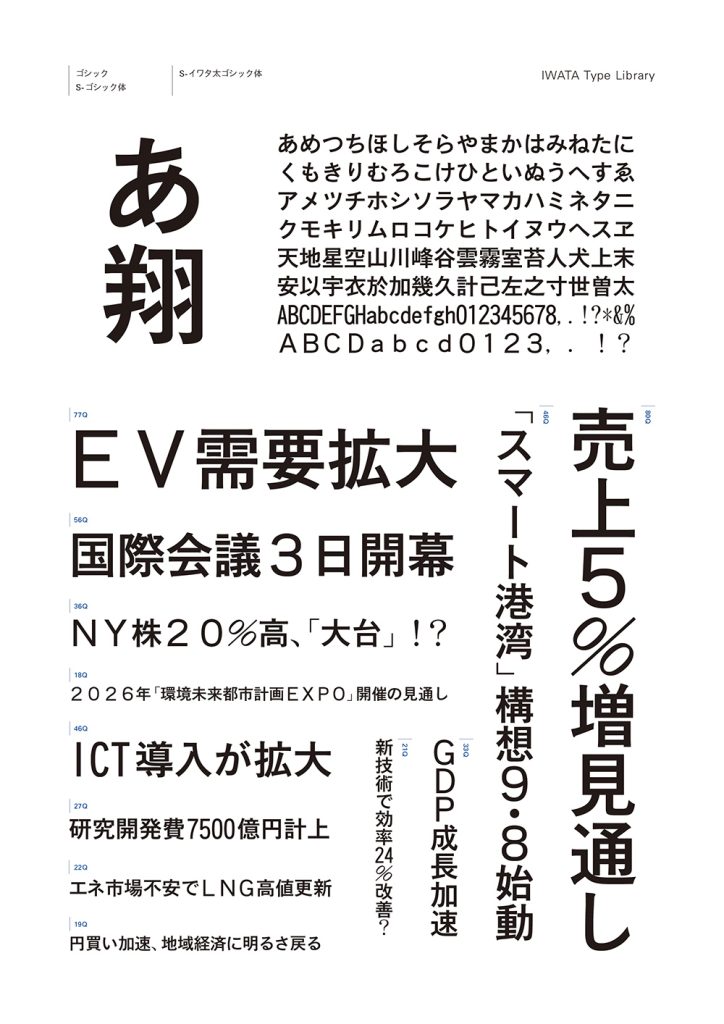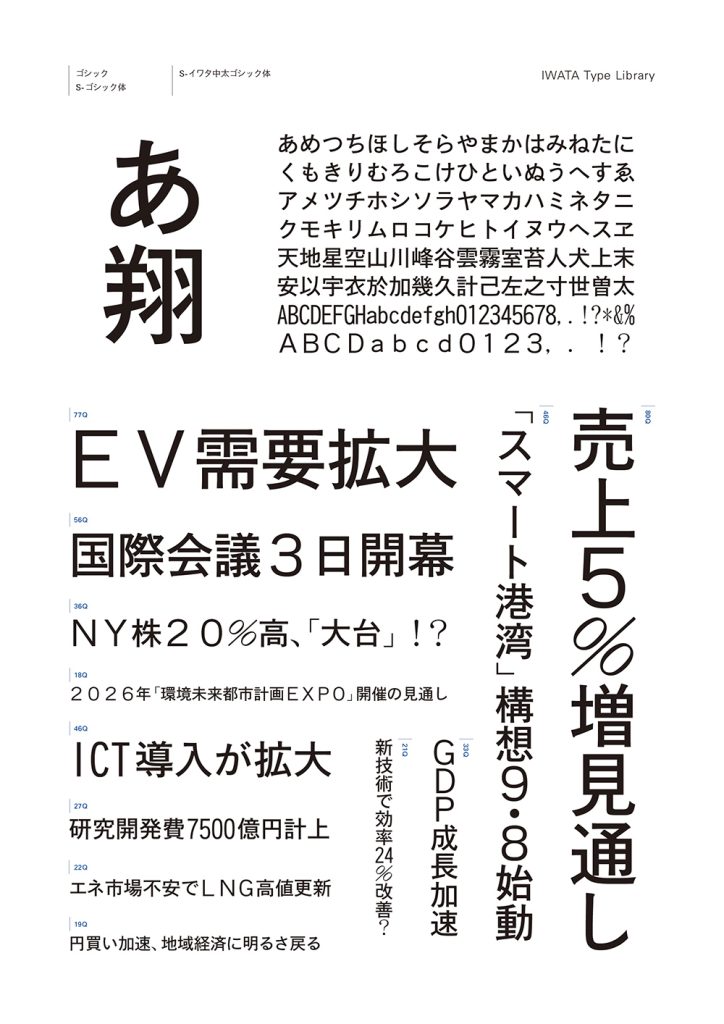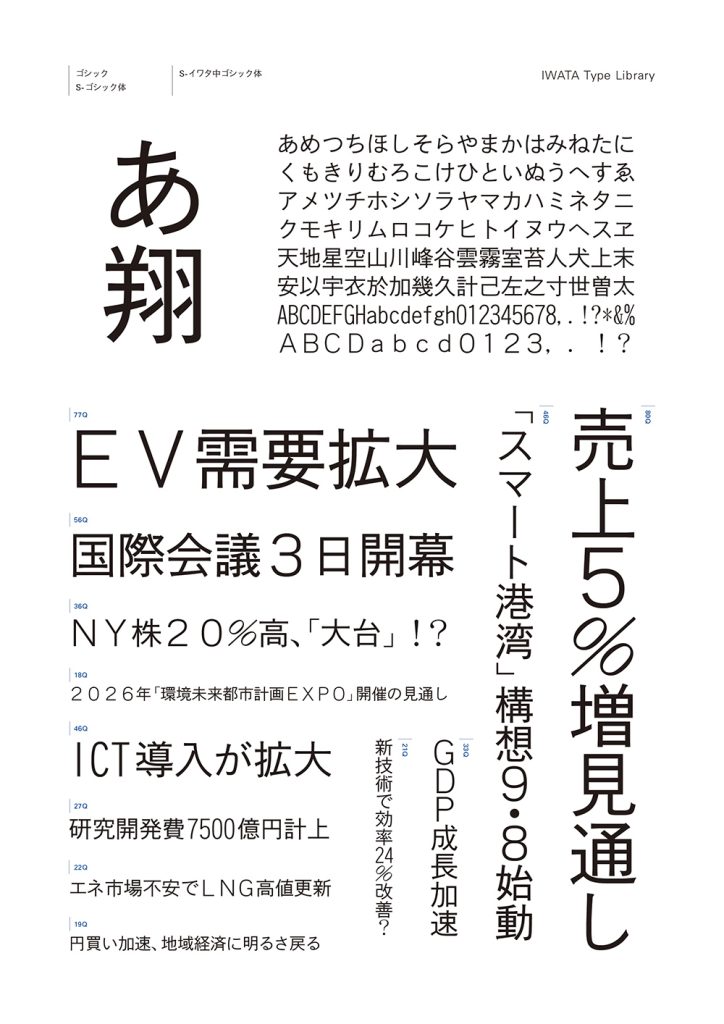
「イワタゴシック体オールド」を新聞見出し用に最適化した書体です。文字セットは共同通信社が策定した「U-PRESS」に独自に調査した拡張文字848 文字を加えた「イワタU-PRESS」に対応しています。
イワタの新聞見出し用書体“S- フォント”とは
約物のデザインや文字の高さなどが、あらかじめ新聞の見出しに最適な状態に調整されたフォントです。細かな調整をせずに美しい見出し組を実現できます。
書体デザインのポイント
新聞の見出し組版に適するよう、デザインに工夫がされています。